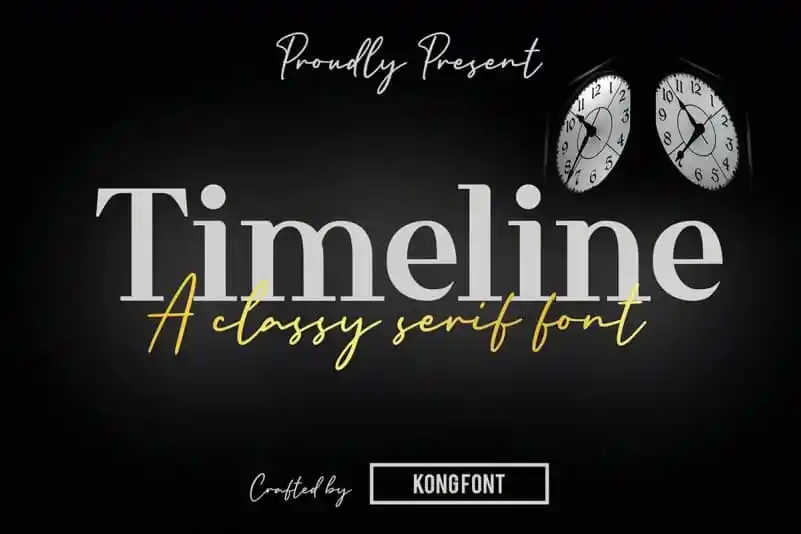
Timeline Serif Font – Download Grátis
Introduzimos a Timeline Serif Font, desenvolvida com uma contraste bem equilibrado entre os troncos finos e as travessas grossas. Sua combinação suave de curvatura e agressividade cria linhas elegantes e confiantes que se destacam especialmente em escala média ou grande. Perfeito para adornar headlines, visual identitário de marca, edição, panfletos, e muito mais. Este font será um complemento valioso no seu arsenal de recursos gráficos, transformando seus projetos digitais de maneira elegante e sofisticada.